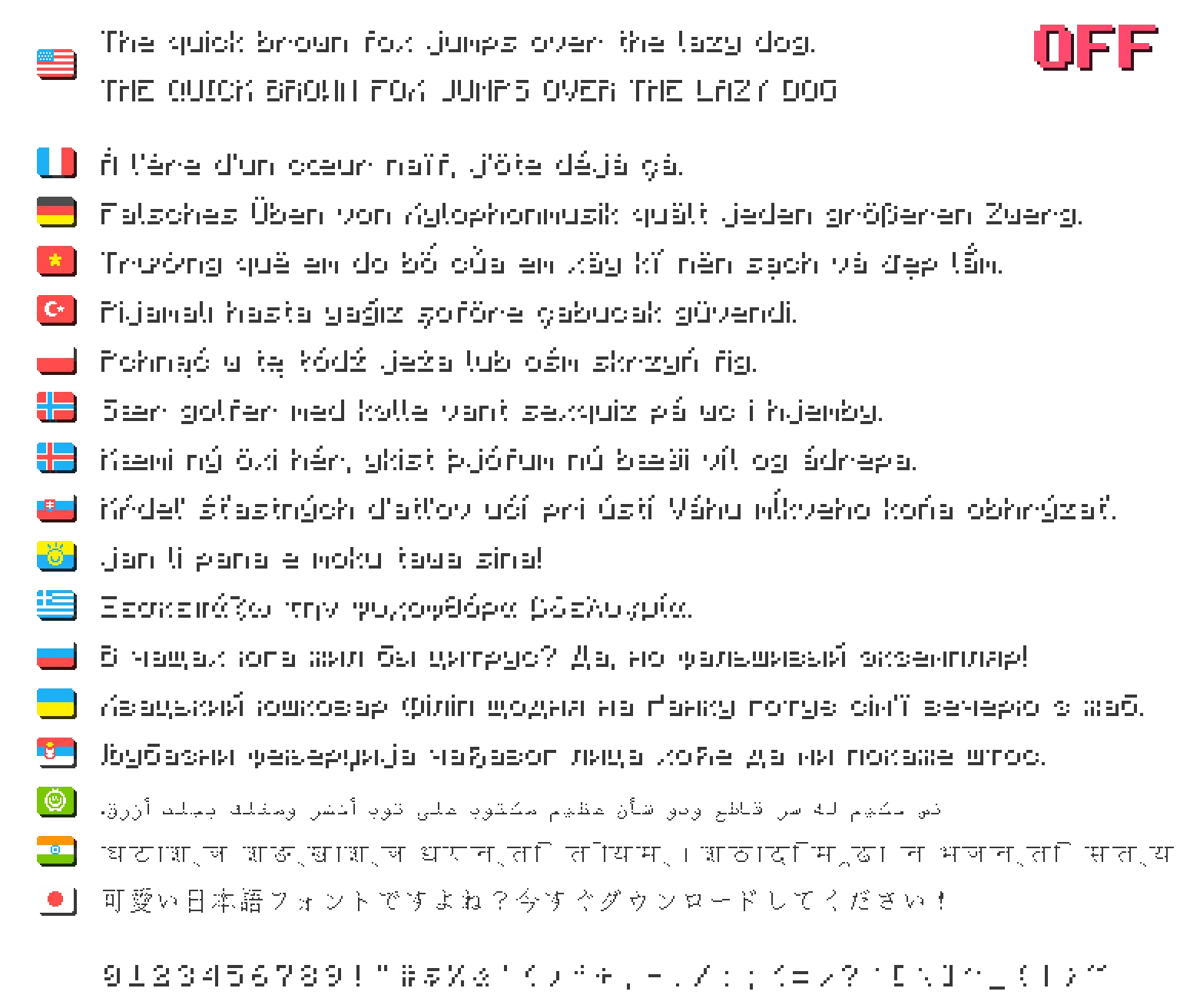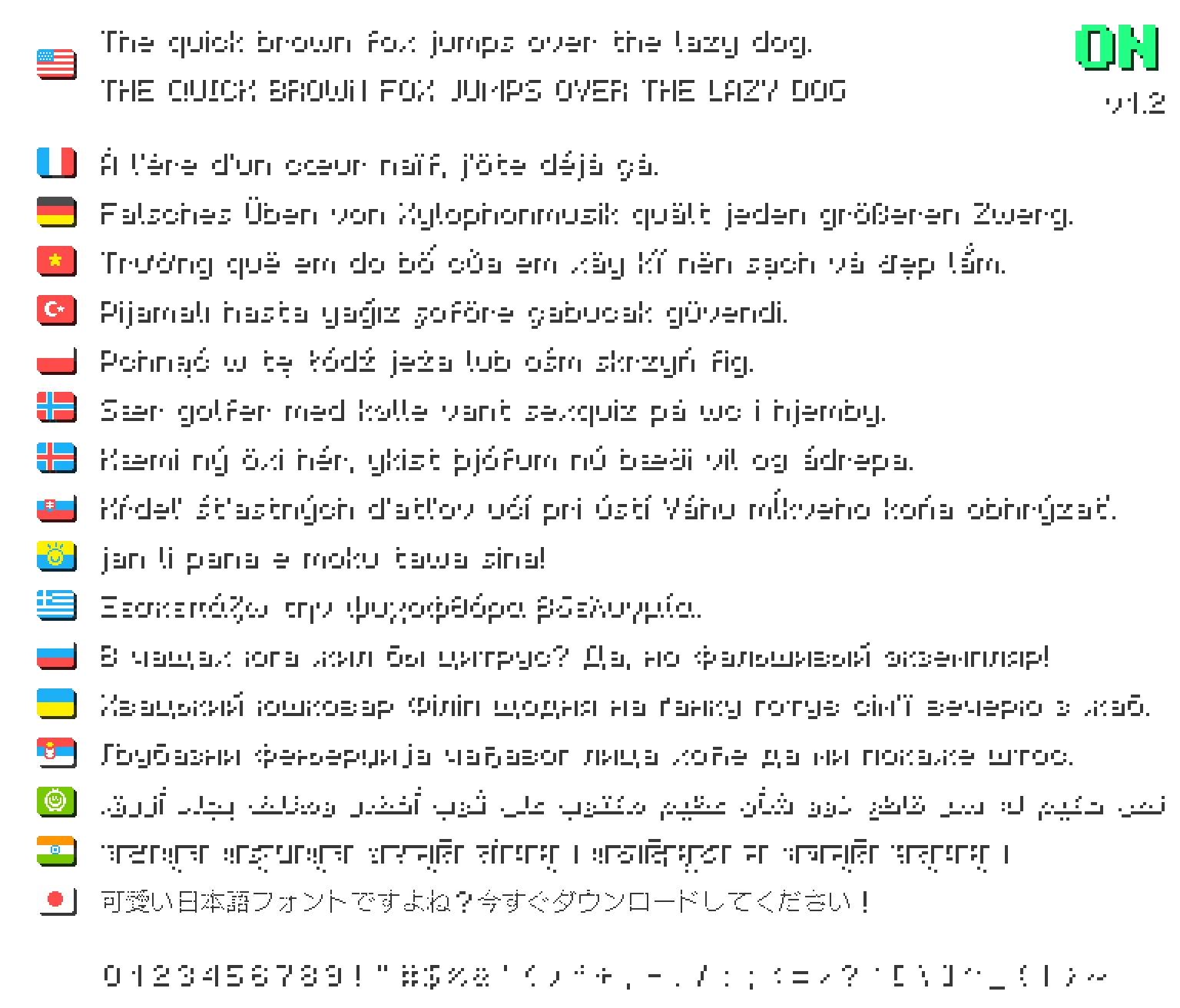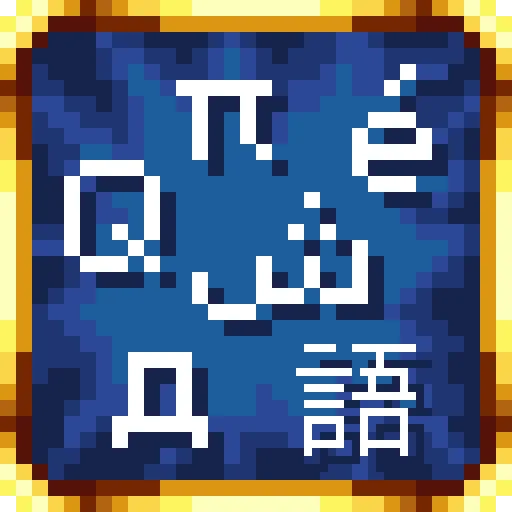
shuriart Font
Плавный и округлый шрифт, улучшающий читаемость и баланс букв. Поддерживает множество языков, включая латиницу, кириллицу, арабский и японский.
Этот ресурспак использует оригинальный шрифт shuriart™ в сочетании с DotGothic16 для повышения чёткости текста. Буквы сделаны более округлыми и плавными, что уменьшает визуальный беспорядок и улучшает баланс веса символов.
Шрифт поддерживает широкий диапазон символов: латиницу (включая вьетнамский, турецкий, польский), греческий, кириллицу (включая русский, украинский, казахский, сербский), арабский (включая персидский и джави), деванагари (для хинди), японский (хирагана и катакана), а также символы IPA, диакритические знаки, математические операторы и стрелки. Также включает изменённый галактический алфавит.